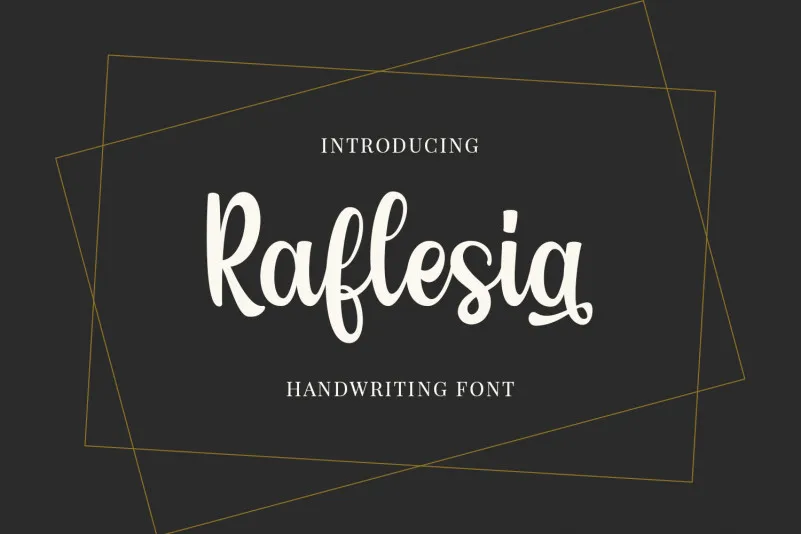
A fonte ‘Raflesia Font’ é uma elegante caligrafia script que traz ao seu design um ar contemporâneo e perfeição na forma. Inspirada nas chamadas antigas de caligrafia, Raflesia oferece um equilíbrio entre finura e grossura, garantindo variedade em cada letra do seu projeto. Não é só sobre a aparência, mas também sobre o equilíbrio perfeito de forma e graça. Essa fonte foi projetada para fazer sua beleza se destacar ainda mais, com uma PUA (Private Use Area) completamente codificada. Isso significa que você terá acesso fácil a todos os gílios e swashes, tornando o processo de inserir essa caligrafia em diferentes formatos de mídia menos trabalhoso e muito mais envolvente. A Raflesia é uma opção perfeita para quem busca adicionar um toque único e elegante aos seus projetos.